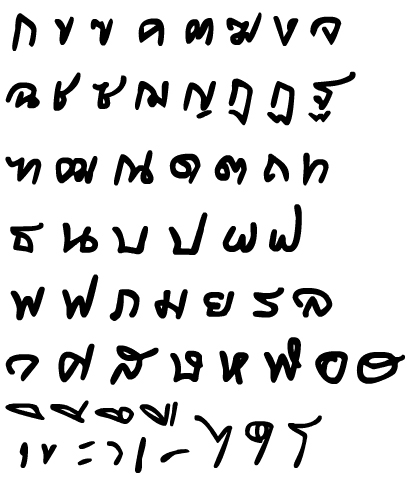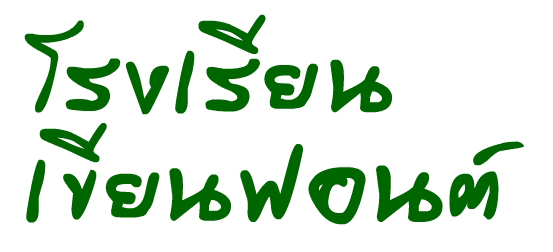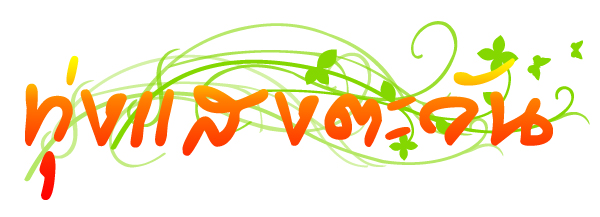
โปรดชี้แนะ
ฟอนต์ลายมือโปรดชี้แนะ    _คาราวะจอกสอง
รู้สึกเหมือนวรเศรษฐ์ครับ
ดังนั้น ทำให้เสร็จเลย ตัวนี้ท่าจะรุ่ง
ดังยักษ์ว่า
รุ่งแน่ๆ
ชอบ วาฬ จัง :12:
ฟอนต์สไตล์เดียวกับฟอนต์วรเศรษฐเลยครับ  :42:
น่าใช้มาก
ลุยต่อเลยค่ะ  :45:
บางอีกนิด ให้บางอีกนิด work!!